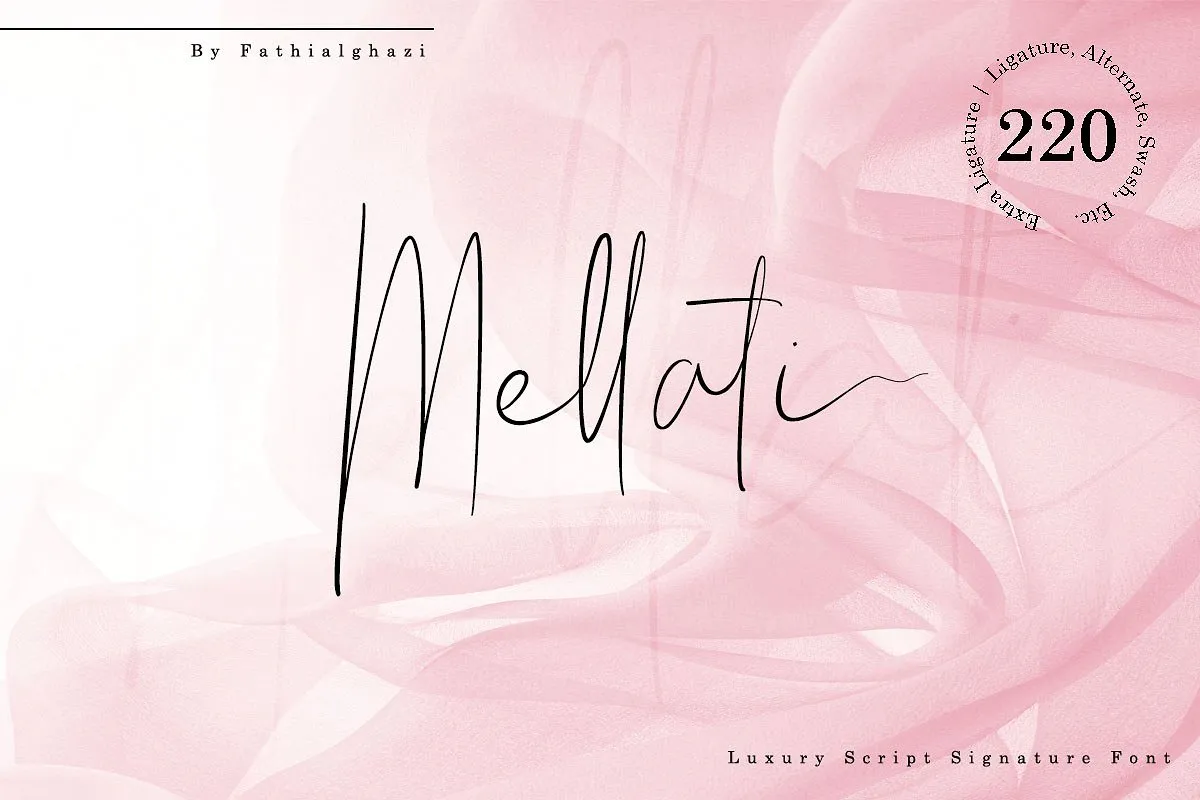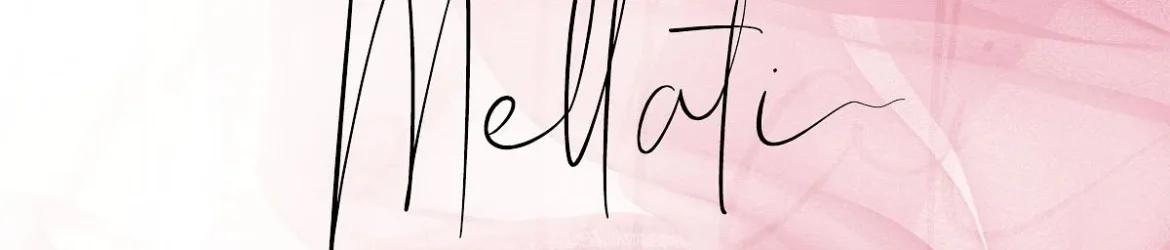
Mellati Signature Font – Download Grátis
Descubra a Mellati Signature Font, uma elegante escolha para designers amadores e profissionais que buscam transparência e naturalidade em suas criações digitais. Esta fonte script é perfeita para estilos de marca, logomarcas, headlines e ideias de salvação de datas, embora seja versátil o suficiente para abraçar conceitos upscale e handcrafted. Desenvolvida pelo designer zziplex, a Mellati Signature Font apresenta uma escrita em script de mão que é facilmente usável. Ela mantém sua autenticidade natural da arte manual, proporcionando uma variedade incrível de ligaturas e alternativas para criar um estilo de assinatura perfeito. Se você está procurando por uma fonte com personalidade única, vibrante e harmoniosa, a Mellati Signature Font é definitivamente o recurso gráfico que procura. Seu design curvilíneo e fluido proporciona uma sensação orgânica na escrita, dando ao assinatura um toque de sofisticação. Este estilo perfeito se adapta a uma variedade de aplicativos, desde logomarcas elegantes até designs de salvação de datas atemporais, sem perder sua essência autêntica e única. A Mellati Signature Font não apenas é ideal para designers que desejam criar um toque pessoal em seus trabalhos, mas também oferece uma alternativa mais sofisticada às escolhas convencionais. Este recurso gráfico é perfeito tanto para aqueles buscando um equilíbrio entre a simplicidade e a complexidade, quanto para aquelas pessoas que desejam transmitir uma mensagem de verdade com cada letra escrita.